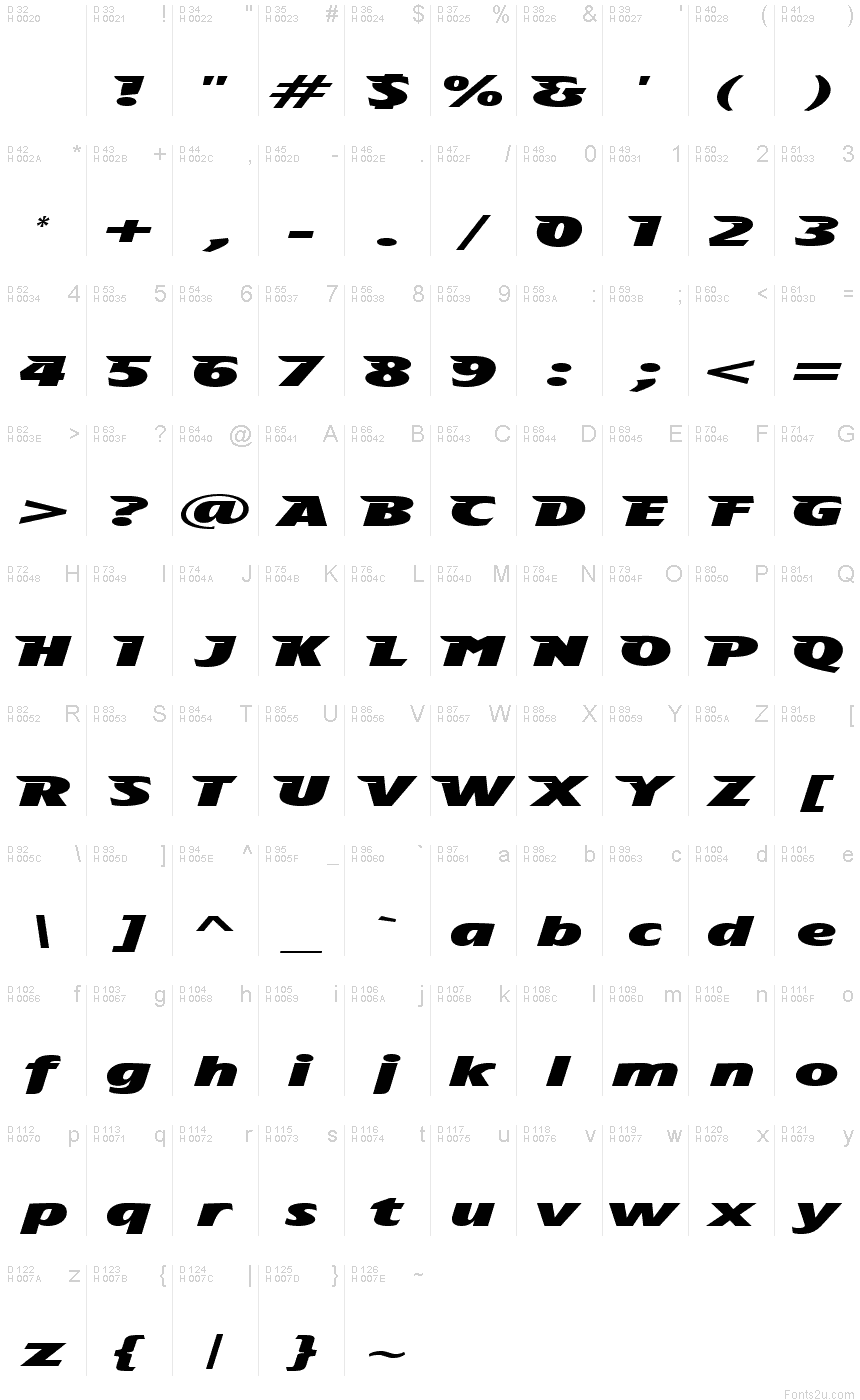
The Aeroplane Flies High Heavy
The Aeroplane Flies High Heavy od The Aeroplane flies high (turns left, looks right) to darmowy retro font display z dynamicznym stylem plakatów z końca lat 70. Litery nachylone do przodu mają szerokie, masywne kształty, łącząc wyraziste krzywizny z ostrymi krawędziami, dzięki czemu krój sprawia wrażenie ciągłego ruchu.
Doskonale sprawdzi się na muzycznych ulotkach, okładkach magazynów, opakowaniach, planszach tytułowych i w projektach logo, gdzie liczy się szybkość i pewny charakter. Ten darmowy font świetnie nadaje się również do krótkich nagłówków i wyróżnionych cytatów, ponieważ przerysowane pochylenie i duża masa własna robią całą robotę za projektanta.